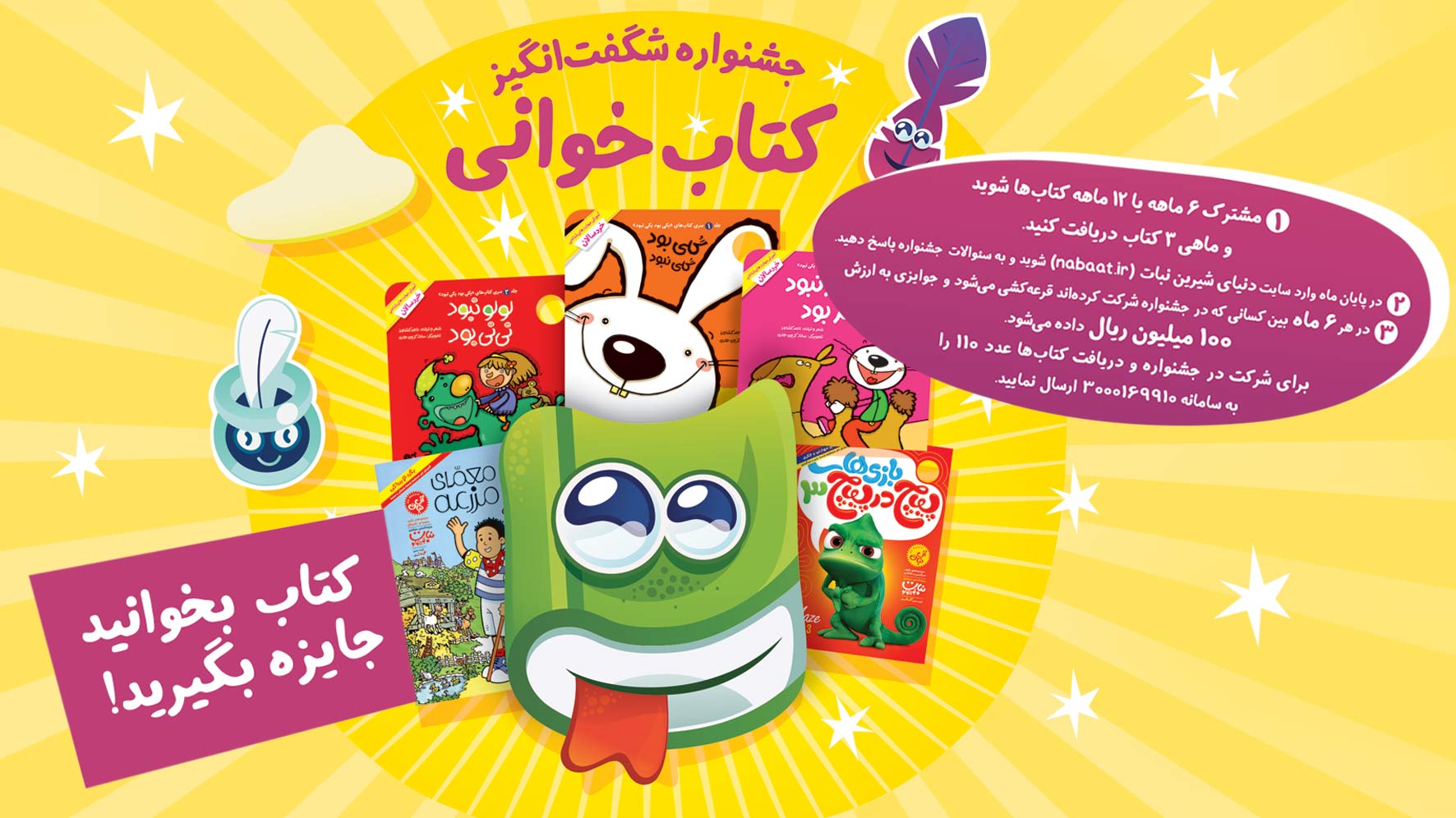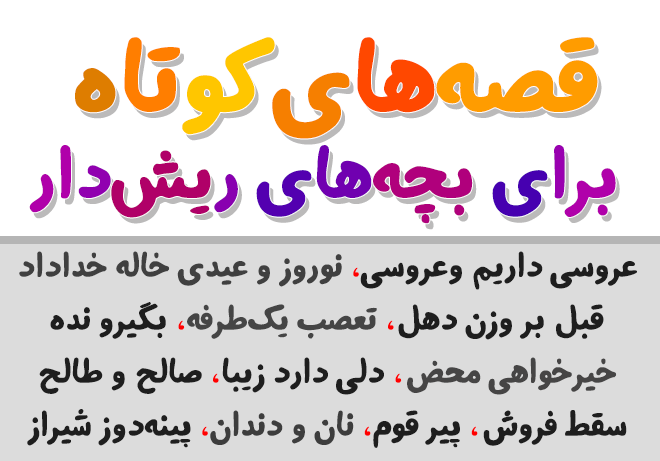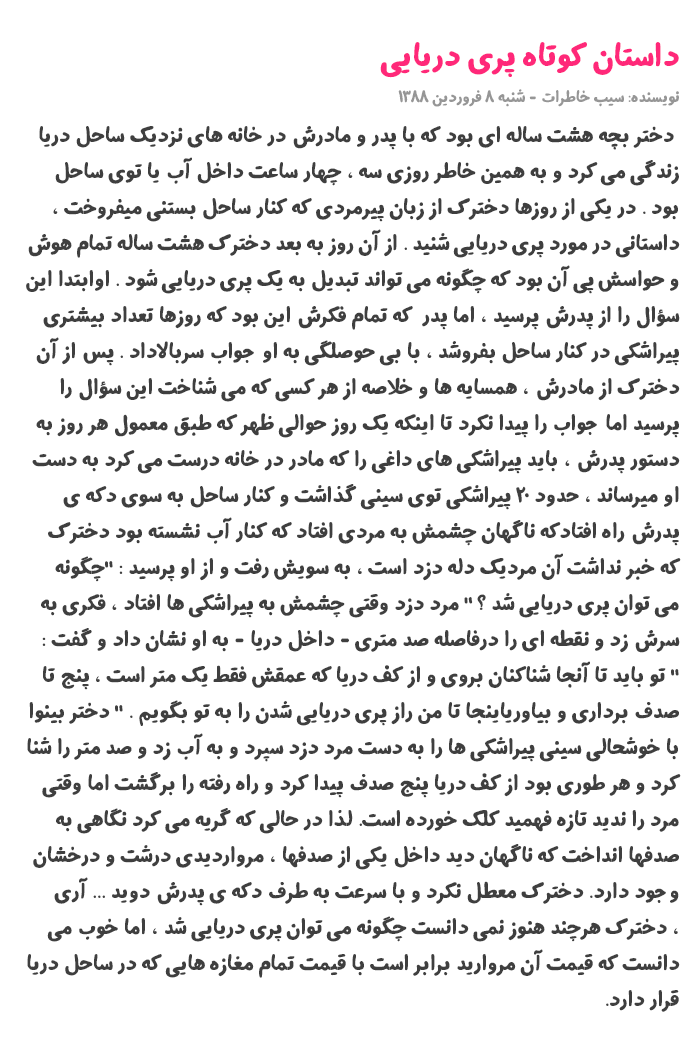
فونت دست نویس محبوبه مهرآور برای موضوعات عامیانه، طنز و ادبیات کودک و نوجوان انتخاب مناسبی است.
بنر مربوط به کتابهای هوشمند نبات
اغلب فونتهای فارسی موجود در سبک دست نویس برای متنهای طولانی مناسب نیستند و بیشتر مناسب نوشتن جملات کوتاه شاعرانه در آثار گرافیکی هستند. اما به کمک این فونت می توان همراه با حفظ حالت دست نویس متنهای طولانی را خواند.